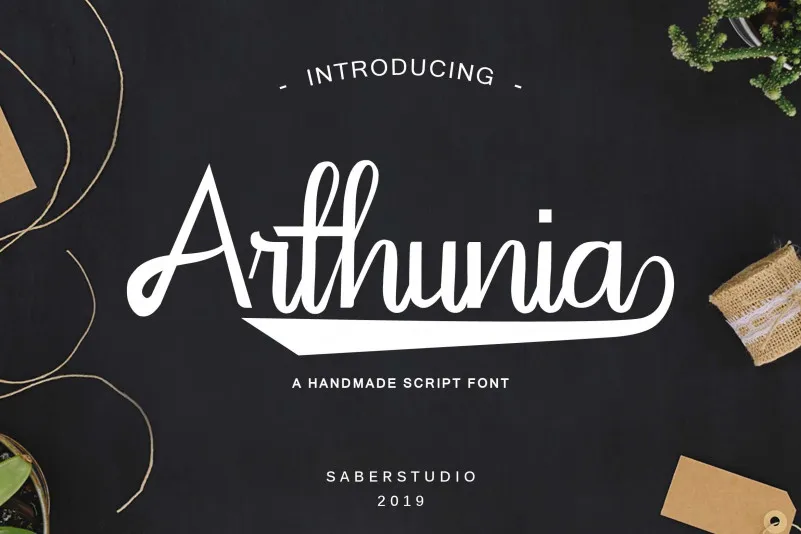
Arthunia Script Font – Download Grátis
A Arthunia Script é uma fonte escrita à mão com um toque único que transmite beleza e modernidade, criada pelo designer didiksaputra. Esta elegante fonte pode inspirar qualquer projeto de design graças a seu ar vintage, deixando-o mais interessante e memorável. Não só é perfeita para aplicativos digitais como banners de redes sociais, mas também combina bem com designs gráficos para revistas ou logotipos empresariais. A Arthunia Script vem em uma versão bold que pode destacar seu texto em qualquer plataforma digital ou impressa, tornando-a um recurso indispensável para designers de todo o mundo.